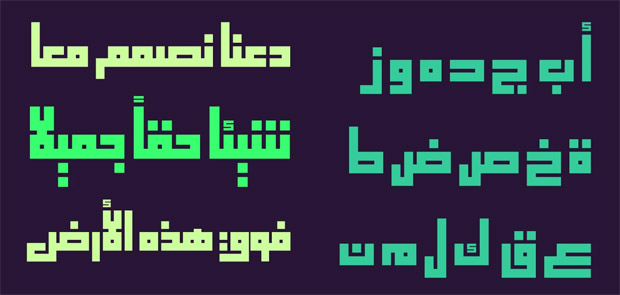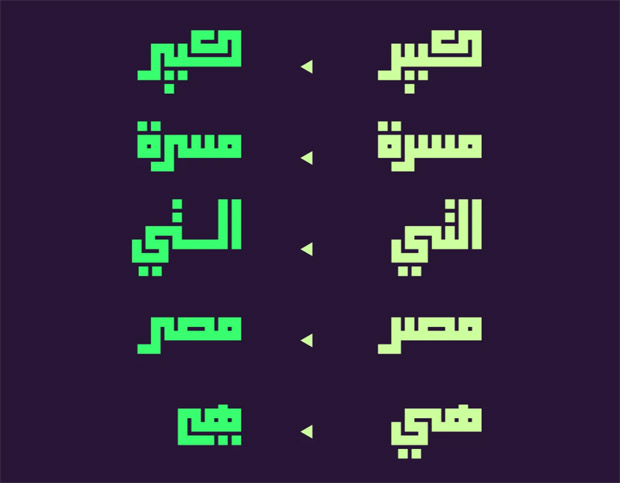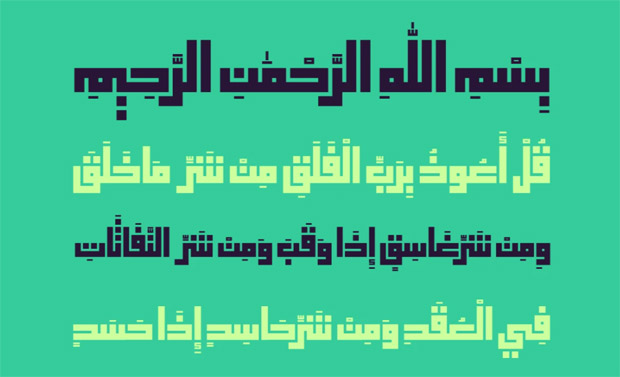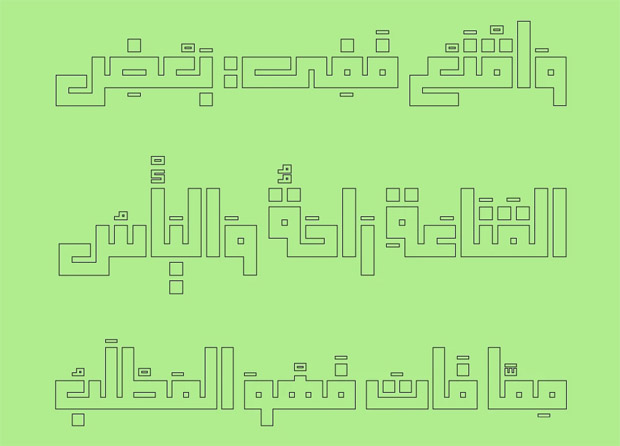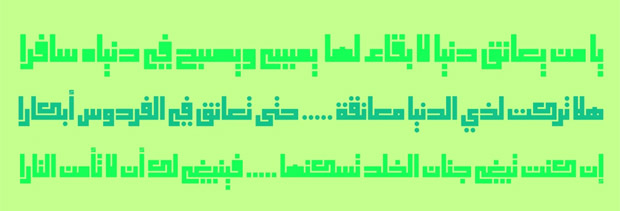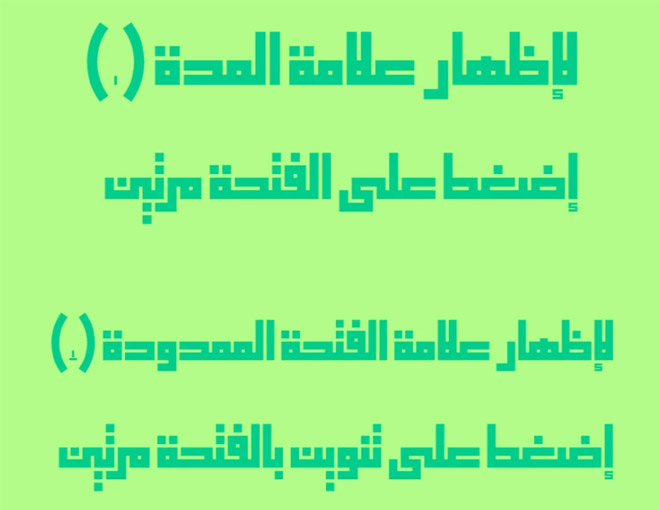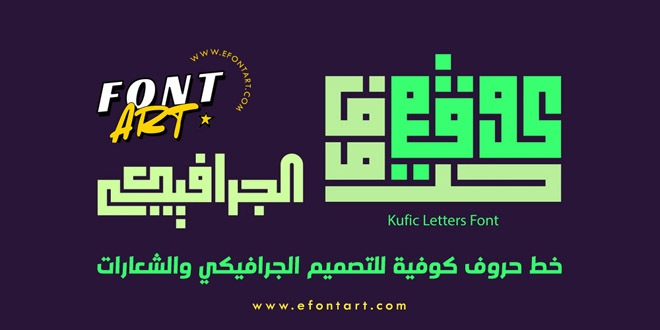
خط حروف كوفية للتصميم الجرافيكي والشعارات
خط حروف كوفية للتصميم الجرافيكي والشعارات .. هو خط كوفي هندسي تمت برمجته وتصميمه وفق قواعد الخط الكوفي المربع، حيث يتكون الخط من (3) أنماط وهي: العادي، نقاط دائرية، محارف مصمتة. كما يحتوي الخط على الكثير من المحارف البديلة والمركبة وبعض المخطوطات التي يمكن استخدامها في التصاميم.